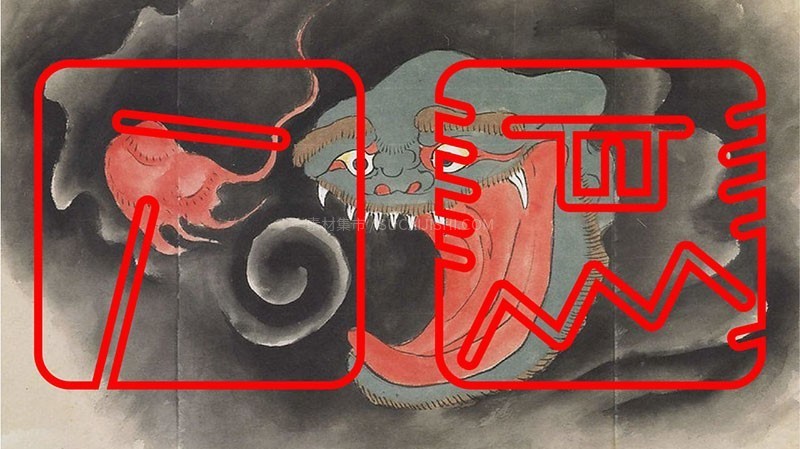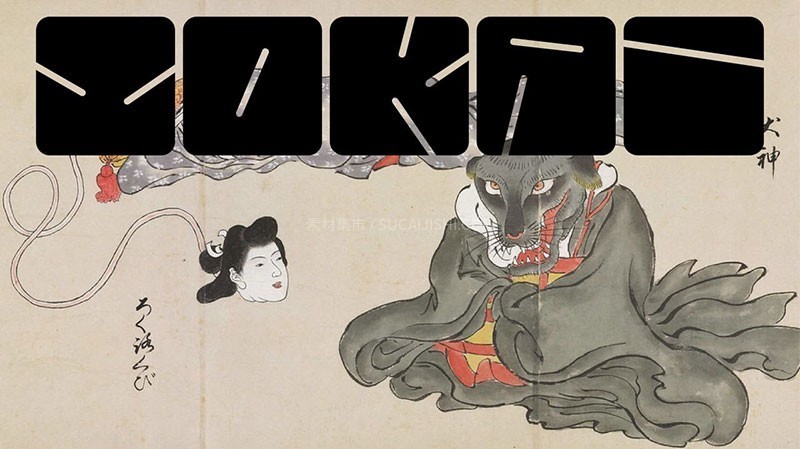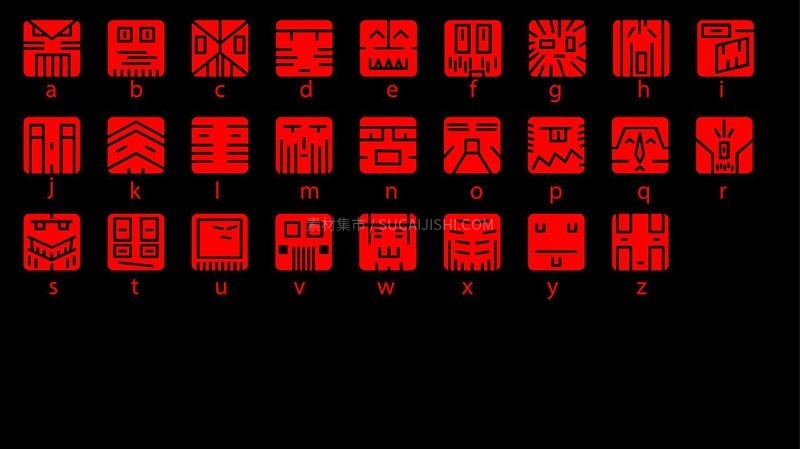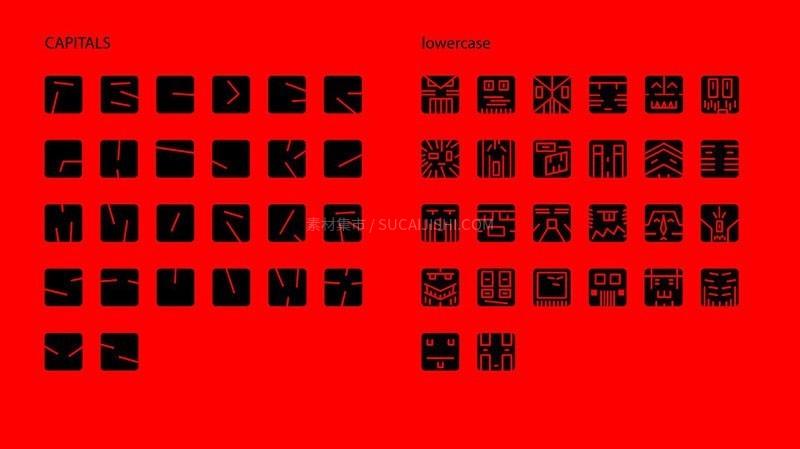
Square Kai 融合日式妖怪美学与极简方正,打造双层视觉语言!
这是一款独特的开放式字体,灵感来源于日本神话中的超自然生物“阳海(yōkai)”和纯粹的方形,完美地提供了一种双层视觉语言。
Square Kai 巧妙地融合了几何极简主义,其大写字母以方形几何图形为基础,构建出简洁、现代的字符。这种独特的设计使其成为大胆标题、海报和数字作品的理想选择,能瞬间吸引眼球,为您的设计注入神秘而现代的独特魅力。
这是一款独特的开放式字体,灵感来源于日本神话中的超自然生物“阳海(yōkai)”和纯粹的方形,完美地提供了一种双层视觉语言。
Square Kai 巧妙地融合了几何极简主义,其大写字母以方形几何图形为基础,构建出简洁、现代的字符。这种独特的设计使其成为大胆标题、海报和数字作品的理想选择,能瞬间吸引眼球,为您的设计注入神秘而现代的独特魅力。